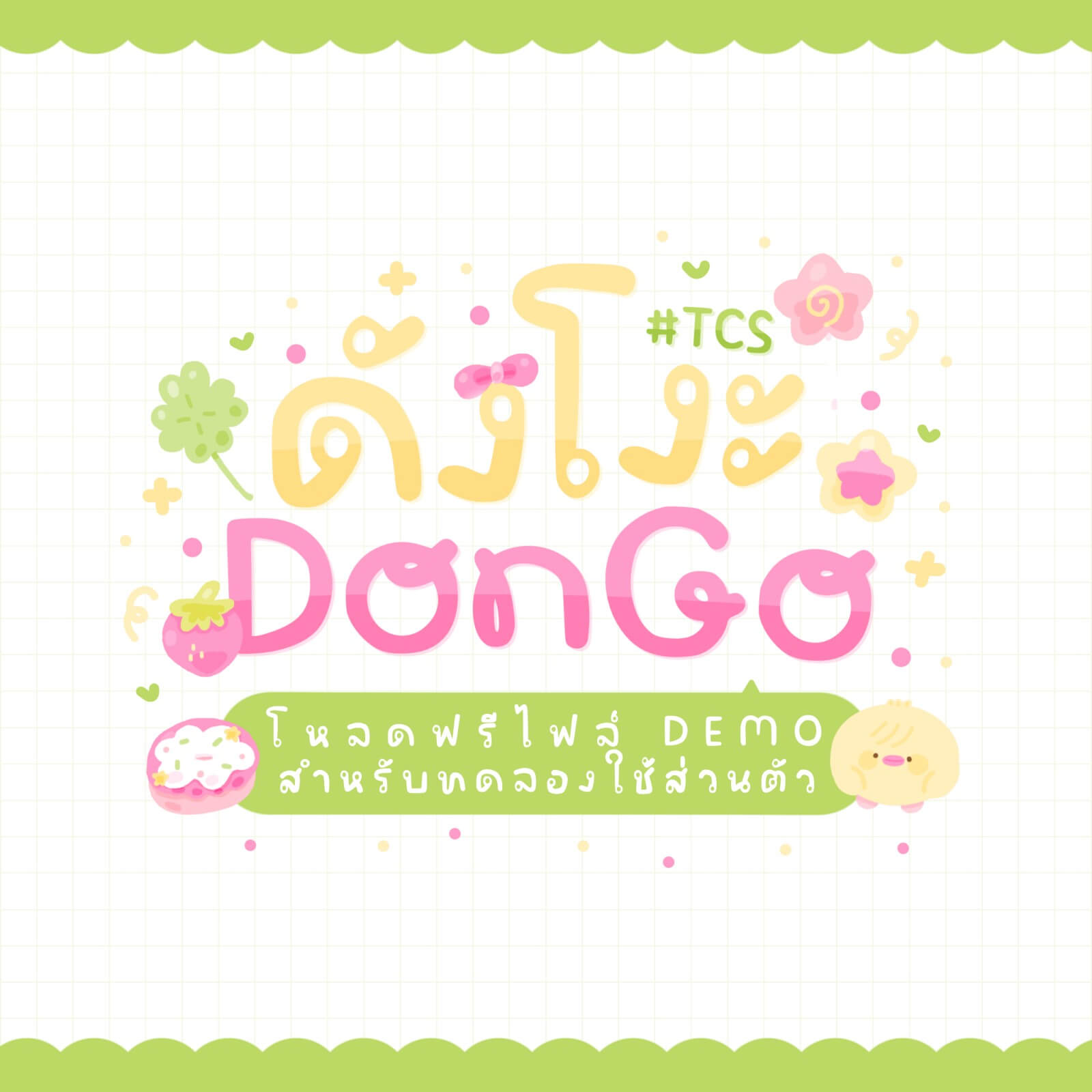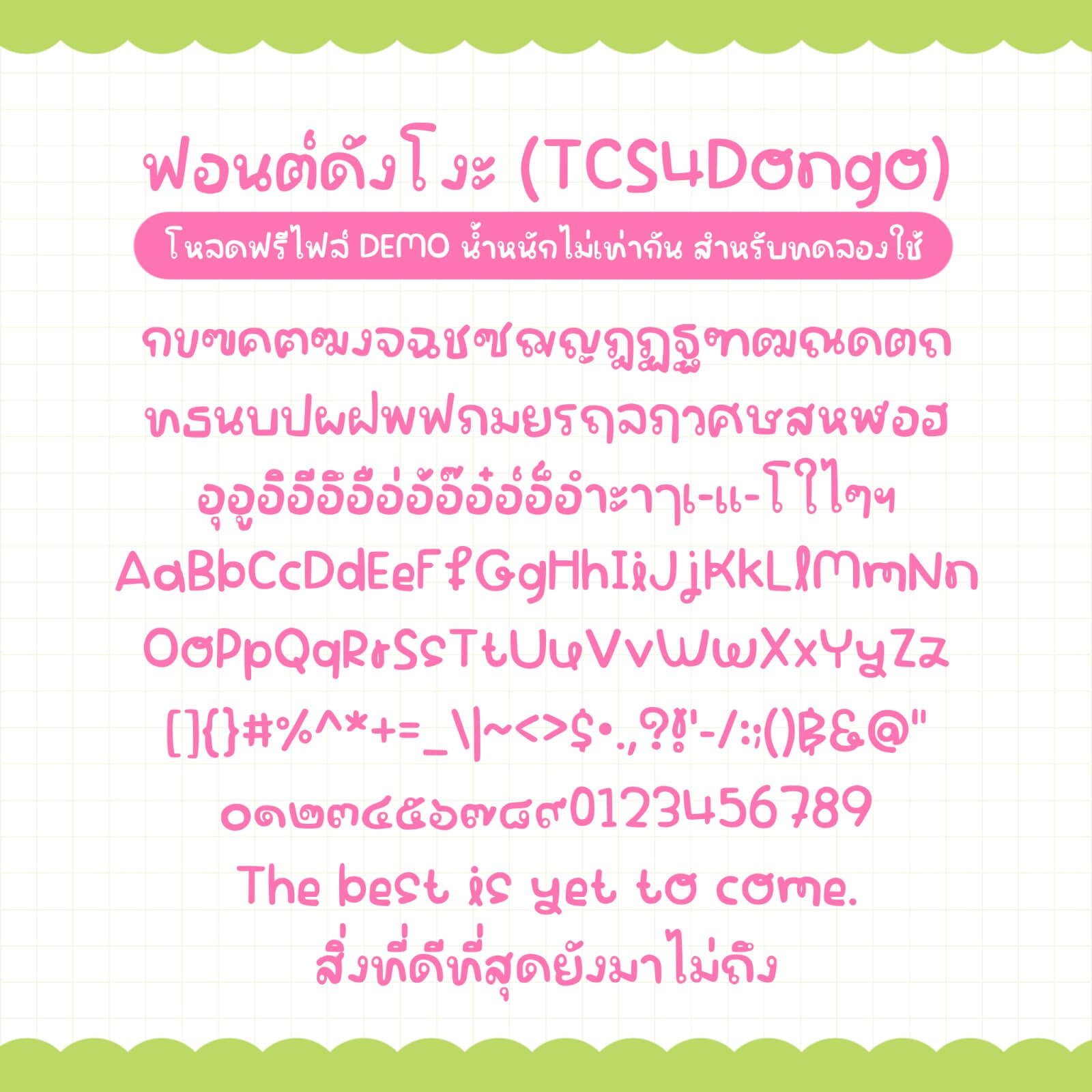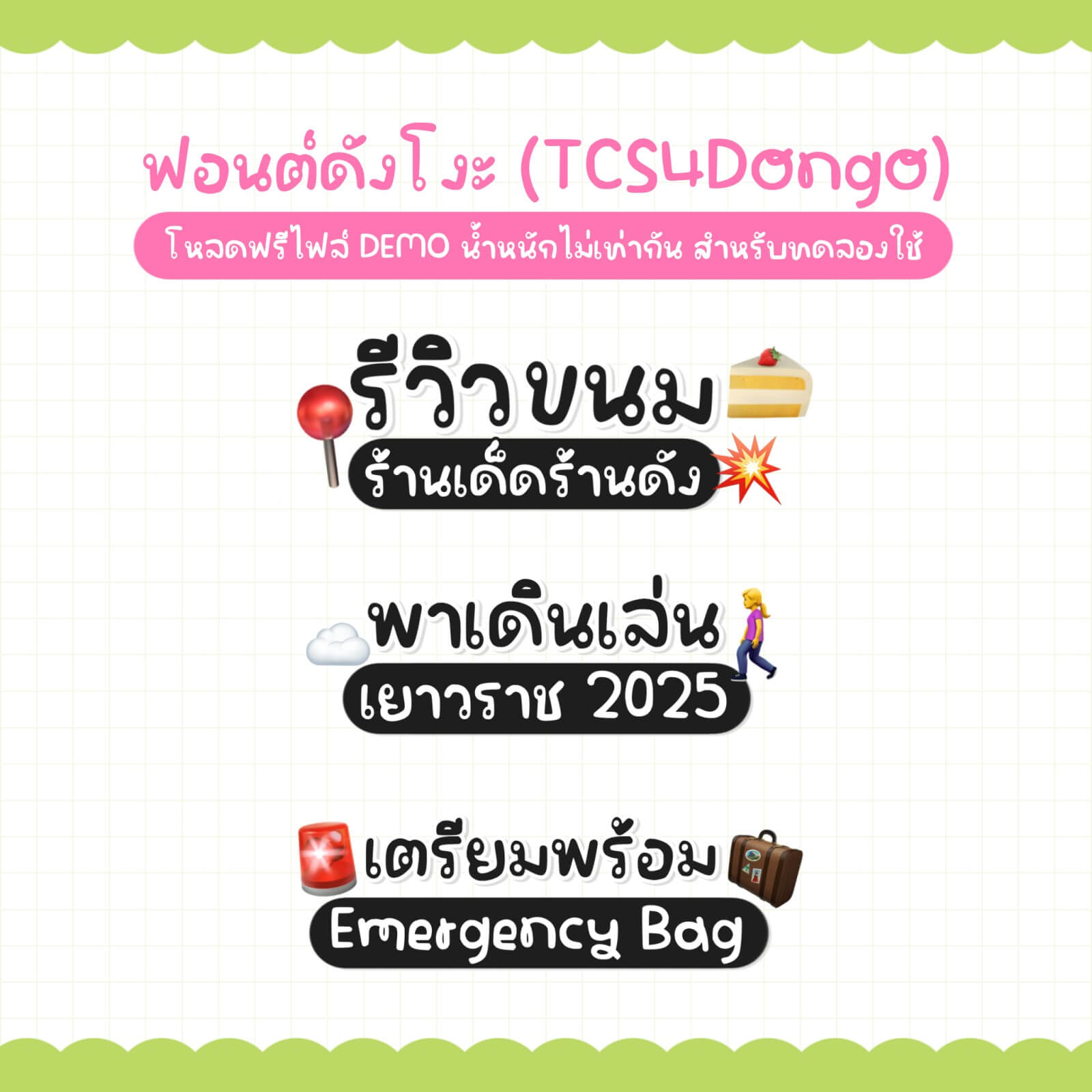
ดังโงะ (TCS4Dango)
ฟอนต์ดังโงะ (TCS4Dango) ฟอนต์สไตล์นี้ ใช้ตกแต่งรูปออกมาได้เป็นธรรมชาติมาก ทำปกคลิปก็ปัง จดโน้ต ตั้งเป็นฟอนต์เครื่องมือถือได้ด้วย
– ไฟล์เวอร์ชันทดลอง (Demo) ยังไม่ปรับสระ มีน้ำหนักไม่เท่ากัน